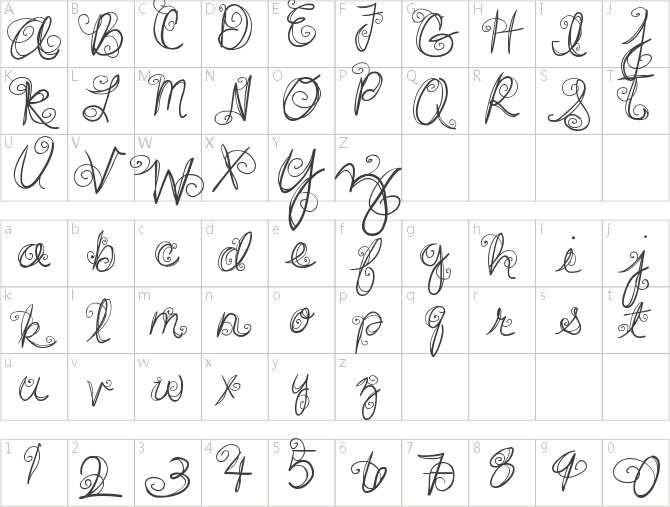
DJB SWIRL ME AROUND 詳情頁
字體名稱: DJB SWI
DJB SWIRL ME AROUND
DJB SWIRL ME AROUND介紹
DJB SWIRL ME AROUND字體字庫是一款讓人賞心悅目、百看不厭的英文字體,適合各類廣告和產品包裝設計應用,字體大小0.04MB,格式為ttf字體,上傳用戶是金百誠,作者/版權方為未知
DJB SWIRL ME AROUND效果圖